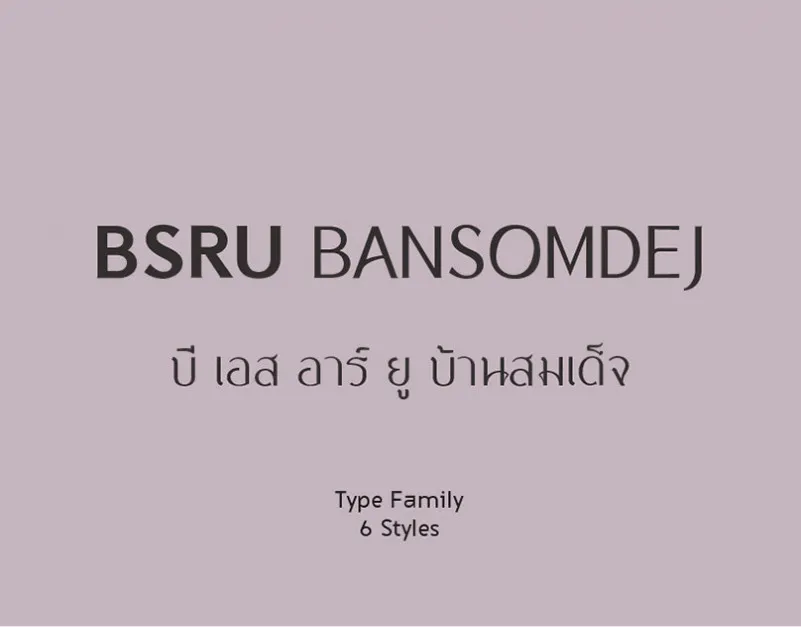
Agradeço por considerar a BSRU Bansomdej Font Family. Esta é uma família elegante de tipo serif moderno inspirada na moda. Ela perfeitamente representa a estética contemporânea e vintage, sendo especialmente bonita quando combinada com uma fonte script. A BSRU é uma família moderna e elegante. O design segue o estilo atual de sans-serif. Esta família também inclui três pesos (Regular, Bold e ExtraBold) e quatro estilos (ExtraBold Italic). Perfeita para cabeçalhos, títulos e citações em qualquer mídia visual onde você deseja introduzir algum tom ou algo único. Funciona especialmente bem em produtos como camisetas, xícaras, bolsas e almofadas.